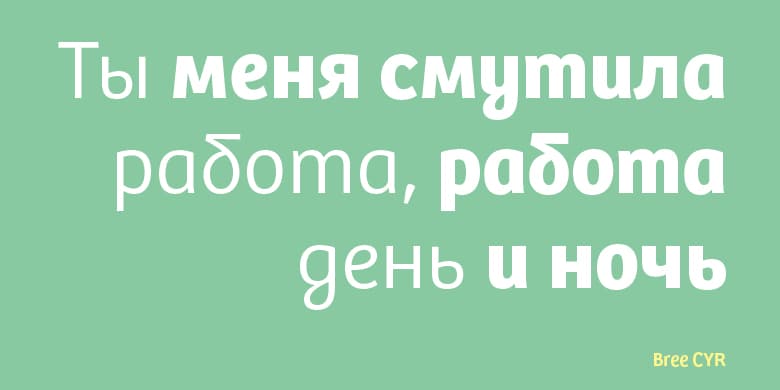
该字体是一款活泼的无衬线字体,为品牌和标题提供了一种活泼的外观和感觉。作为一款直立的斜体,Bree展示了不招摇的大写和更生动的小写字母的悦目组合,给予了文本生动的视觉体验。Bree显示是受到了一些的顽皮风格影响,这意味着它非常有个性。
Bree is a spry sans serif that delivers a spirited look and feel for branding and headline usage. As an upright italic, Bree shows a pleasant mix of rather unobtrusive capitals with more vivid lowercase letters, giving text a lively appearance. Bree is clearly influenced by handwriting with a touch of cheekiness, which equals a big personality.